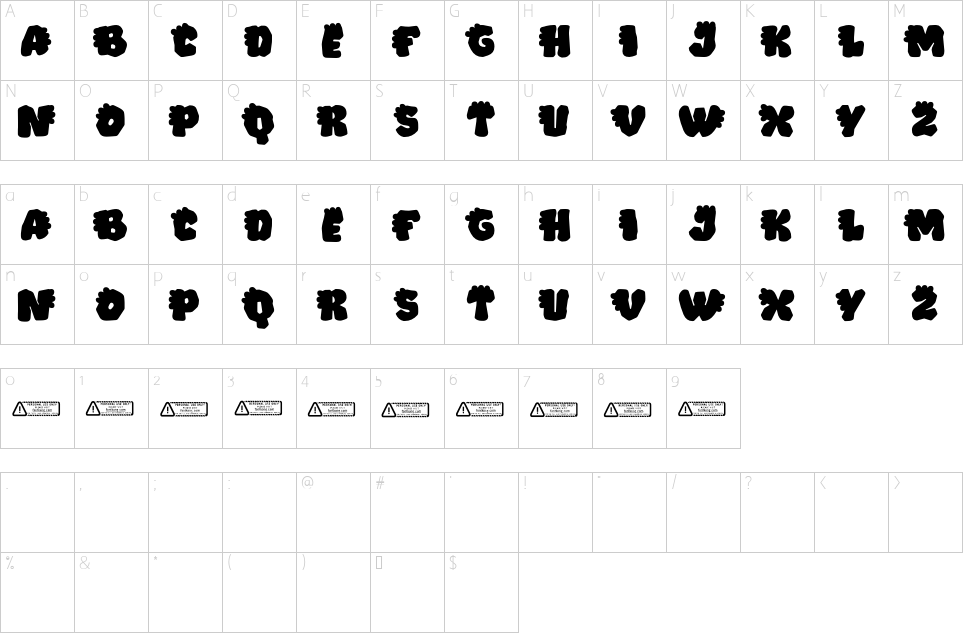
Aqui está uma descrição envolvente para a página de download da font ‘Dino Roar Font’, mantendo a consistência com as instruções: Descubra a Dino Roar, uma fonte única e vibrante que chama atenção nos documentos, sites e aplicativos. Desenvolvida pela Font Kong, esta font é ideal para quem busca algo distintivo em sua tipografia. As formas dinâmicas e o estilo único desta font fazem dela um recurso útil para qualquer designer ou editor de texto online. Com design moderno e sofisticado, a Dino Roar se destaca entre as diversas opções disponíveis para os usuários do Windows e Mac. Descubra por si mesmo porque essa font pode ser o diferencial em seus projetos digitais. Descarregue a Dino Roar hoje e dê um toque especial ao seu trabalho, seja ele um documento simples ou um design complexo. Não espere mais – adquira sua própria cópia da Dino Roar para inovar na maneira como você expõe suas ideias online.